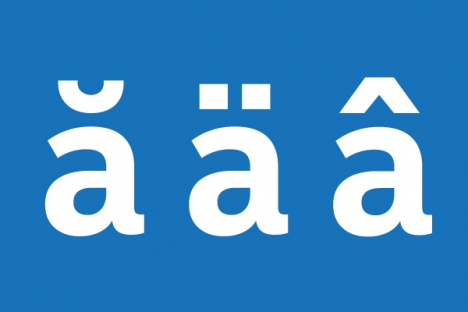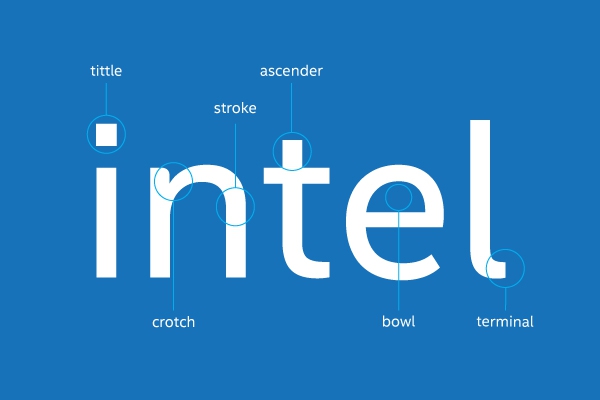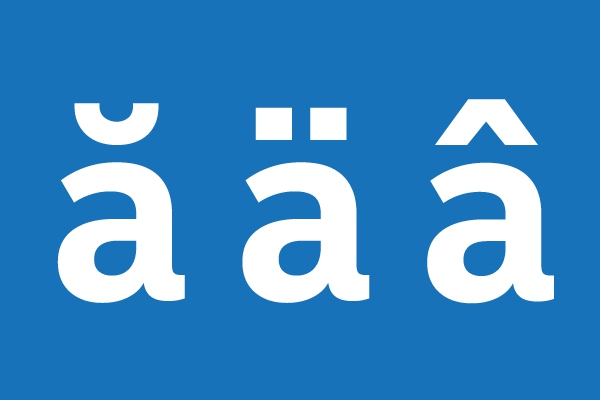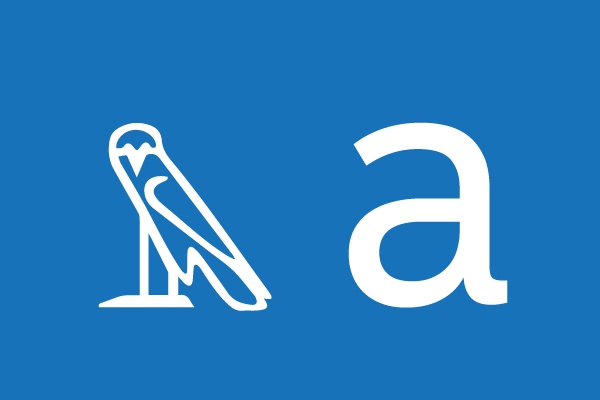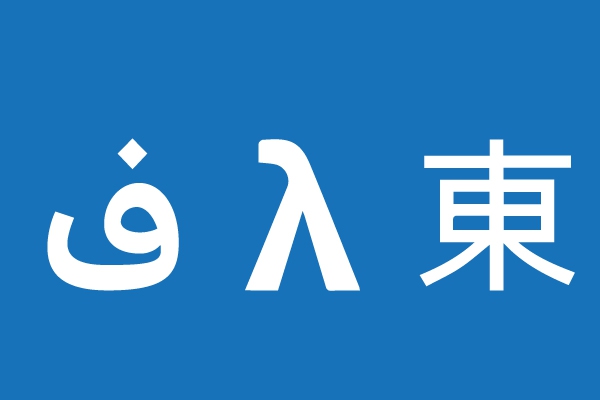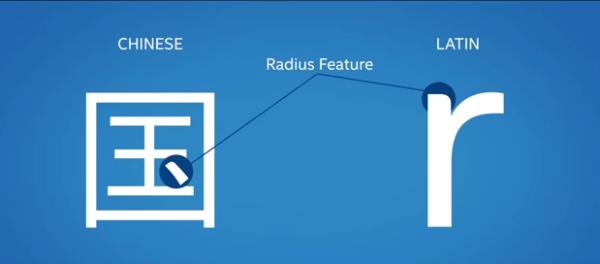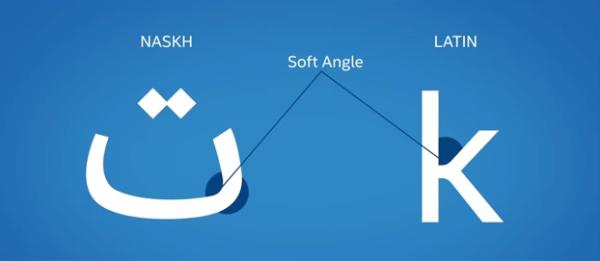
Intel изменила шрифт в логотипе впервые за многие годы. Работу для корпорации провели брендинговое агентство Red Peak и студия шрифта Dalton Maag. Новый шрифт легко можно будет прочитать на всех медиа- платформах и различных языках, обещают креаторы.
Старый логотип был доступен только на латинском языке и не был читабельным на гаджетах. Новый шрифт должен обеспечить компании единый и упрощенный взгляд на всех каналах связи.
«Intel нужен был шрифт, который бы смог прочитать пятилетний ребенок и 80-летний старик не только на бумаге, но и на экранах мобильных устройств», - пояснил креативный директор проекта Бруно Мааг.
Агентство работало над проектом в течение года, продумывая дизайн логотипа и шрифт, который бы раскрывал в себе идеи открытости и жизнелюбия. Следуя этой идее, компания избавилась от острых углов в и отдали предпочтение округлостям и мягким углам. В итоге получившуюся работу назвали «Intel Clear».
Старый логотип